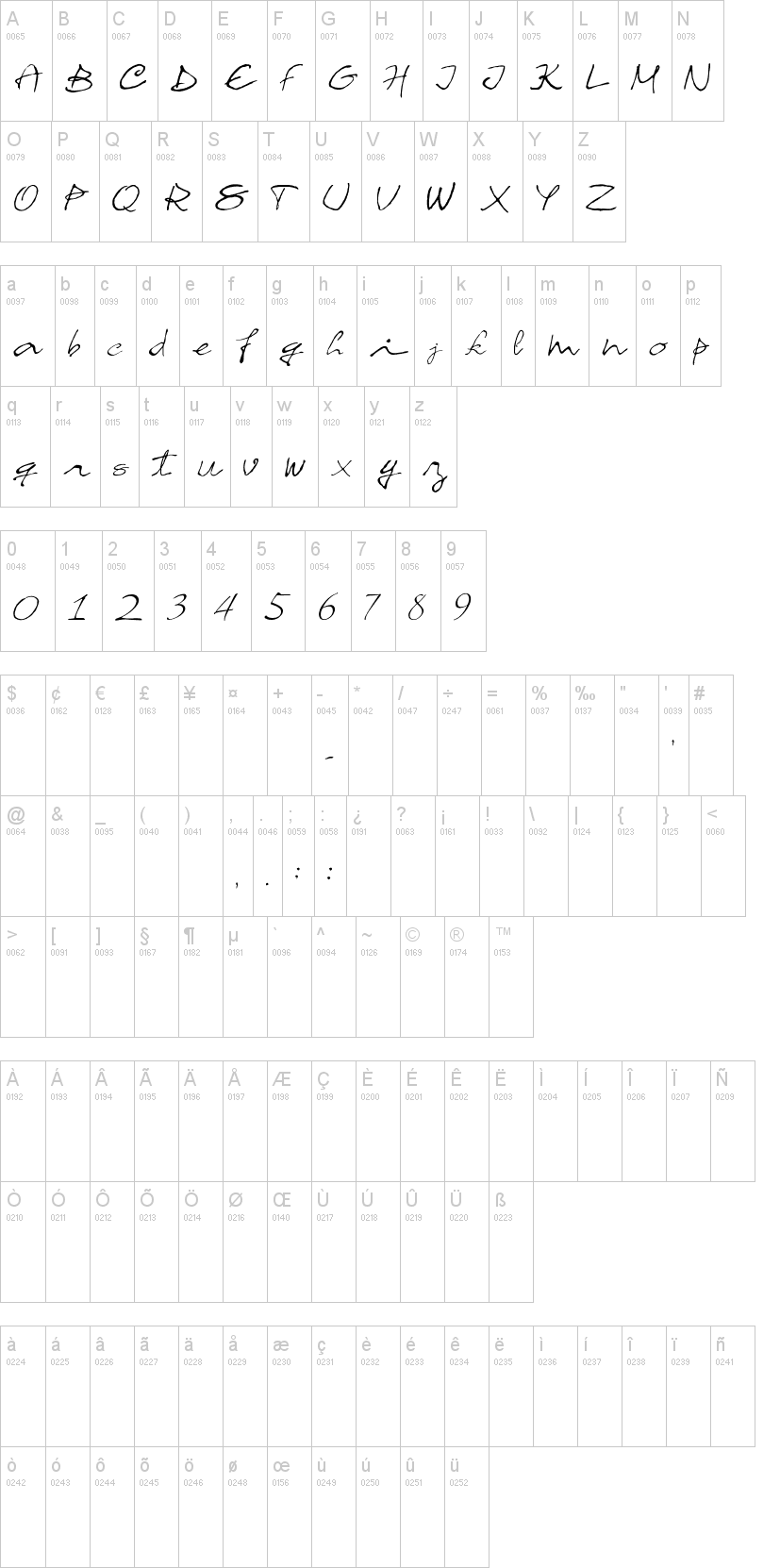
很抱歉,我不确定您所提到的“Chacross Script”字体是指哪个具体的字体。不过,关于脚本字体,我可以提供一些基本的信息。 脚本字体是一种手写风格的字体,通常用于设计卡片、海报、书籍封面等需要艺术感和个性化的项目中。脚本字体的特点是每个字母都有独特的笔划和连笔,呈现出一种柔和、流畅的视觉效果。脚本字体通常分为两种类型:连接脚本和不连接脚本。 连接脚本字体的特点是字母之间有连接线,看起来像是一条连续的线条。这种字体常用于婚礼、纪念日等场合的设计。 不连接脚本字体的特点是字母之间没有连接线,每个字母看起来都是独立的。这种字体常用于卡片、海报等需要注重可读性的设计。 希望这些信息对您有所帮助。内容介绍
Chacross Script是一款非常不错的手写艺术字体,具有很好的视觉感,适合于文化类的宣传设计、商业类品牌的广告和产品包装设计以及个性化文字排版等较多场景。